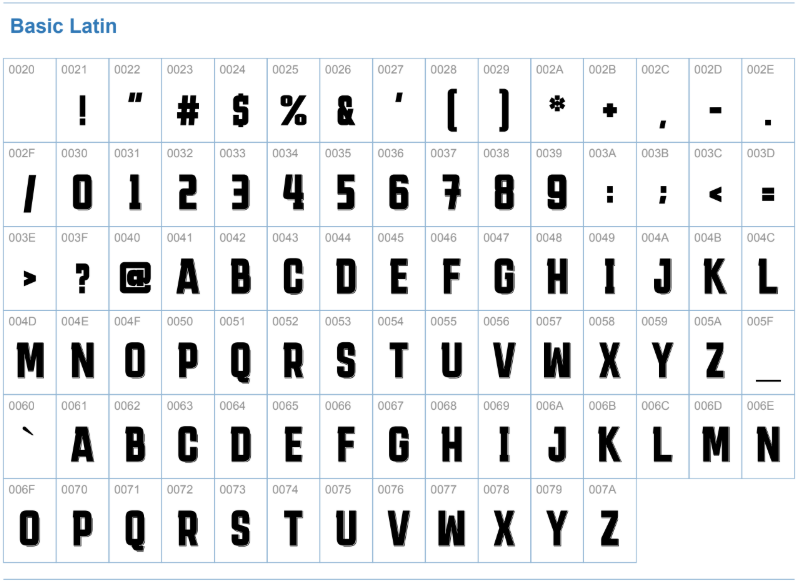
A Seleção de Israel entra em 2026 com uma identidade visual completamente reformulada. Mais do que o novo escudo e as camisas que já viralizaram nas redes, o grande destaque gráfico da temporada é a tipografia oficial, desenvolvida para traduzir o peso da herança cultural e a ambição esportiva da equipe dentro e fora dos gramados.
A fonte exclusiva chega carregada de personalidade e já caiu nas graças de designers e torcedores que acompanham cada detalhe do material esportivo. Seja para criar artes de torcida, homenagens ou projetos digitais, a tipografia do time nacional virou item obrigatório para quem respira futebol e design.
Estilo visual da tipografia
A fonte mescla tradição e modernidade em cada caractere. Os números são ligeiramente condensados, com terminações angulares que lembram inscrições antigas ressignificadas para o futebol contemporâneo. Os traços possuem espessura variável — detalhe que cria movimento mesmo em composições estáticas.
A legibilidade foi pensada especialmente para transmissões em TV e leitura rápida nas arquibancadas. Por isso, a distância entre caracteres evita qualquer ruído visual, mantendo a clareza mesmo nos uniformes em velocidade de jogo.
Aplicação no uniforme
No manto Home, a tipografia aparece em branco com contorno azul celeste, aplicada sobre o fundo azul Royal. O número ganha presença dominante nas costas, enquanto o nome segue o arco superior com espaçamento preciso.
Na camisa Away, a fonte assume o protagonismo em tom azul escuro contrastando com o branco limpo da base. Já o terceiro uniforme Third traz aplicação em dourado metálico, reforçando o caráter premium da coleção 2026.